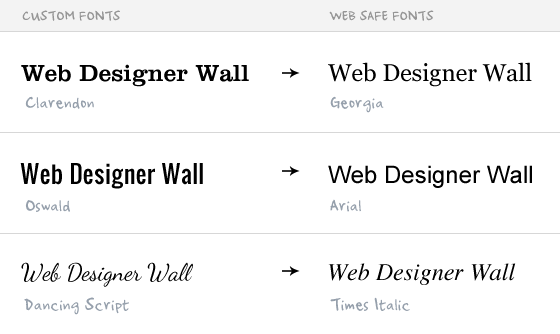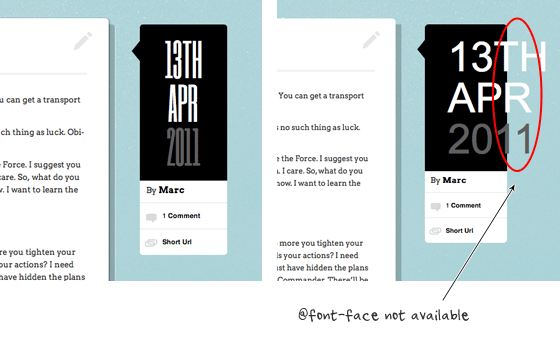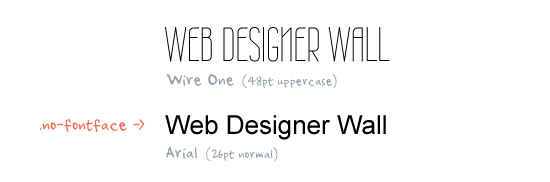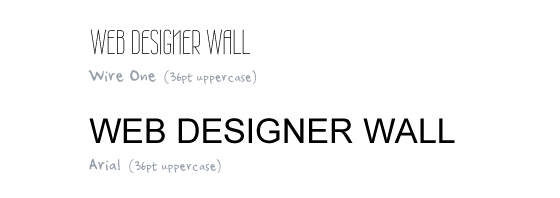
Использование свойства CSS3 @font-face
Хотя свойство @font-face поддерживается большинством браузеров, например, браузерами Internet Explorer, Firefox, Chrome и Safari, есть и исключения. И когда это свойство не поддерживается, то нестандартные шрифты могут испортить верстку или привести к другим нежелательным последствиям. В этом уроке мы расскажем о распространенных сложностях, возникающих при использовании нестандартных шрифтов и подборе запасных шрифтов, присутствующих во всех системах, и покажем, как создать отличные запасные шрифты с помощью библиотеки JavaScript под названием Modernizr.
Распространенная ошибка
Одной из распространенных ошибок при использовании нестандартных шрифтов является то, что многие не определяют запасные шрифты или выбирают неподходящие запасные шрифты.
Запасные шрифты
Присутствующие во всех системах шрифты для обходного пути
При использовании нестандартных шрифтов важно добавить присутствующие во всех системах шрифты в качестве обходного пути. Такой запасной шрифт поможет Вашему дизайну приемлемо выглядеть, когда свойство @font-face не поддерживается или не доступно. Самое важное при выборе запасных шрифтов — выбрать присутствующие во всех системах шрифты, которые наиболее близки к нестандартному шрифту. Например, если нестандартный шрифт — Clarendon, то наилучшим присутствующим во всех системах запасным шрифтом будет Georgia, так как оба эти шрифта с засечками, и у них примерно одинаковая ширина символа.
Сложности с версткой
Так как у каждого шрифта свои ширина, высота, толщина, расстояние между символами и т. д., то некоторые шрифты невозможно заменить присутствующими во всех системах шрифтами. Давайте рассмотрим пример ниже. Это сравнение нестандартного шрифта Wire One и присутствующего во всех системах шрифта Arial размера 36 точек и всеми заглавными буквами.
Это может вызвать сложности с версткой, показанные на изображении ниже, где запасной шрифт вылазит за границы.
Modernizr
К счастью, библиотека JavaScript под названием Modernizr может помочь решить вышеописанные сложности. Modernizr — это библиотека JavaScript, которая определяет, какие свойства CSS3 поддерживаются браузером. После чего добавляется класс CSS в элемент <html>, чтобы показать, поддерживаются ли свойства. Например, если свойство @font-face не поддерживается, добавится класс no-fontface в элемент <html>, т. е. <html class="no-fontface">. Эти классы CSS добавляются с помощью JavaScript, они не видны в исходном коде. Чтобы увидеть их, нужно исследовать элемент страницы или посмотреть созданный код.
Запасные шрифты с помощью Modernizr
Демонстрация работы
Так что мы можем использовать библиотеку JavaScript под названием Modernizr, чтобы определить, поддерживается ли свойство @font-face, и после этого задать подходящие запасные шрифты. Например, можно задать стили для запасных шрифтов, такие как размер, расстояние между символами, толщина, преобразование текста и т. д, чтобы они были наиболее похожи на используемый нестандартный шрифт.
Подключение Modernizr
Стили CSS для класса .no-fontface
После этого нужно добавить дополнительные правила, определяющие стили для класса .no-fontface. Посмотрите пример, чтобы увидеть окончательный результат.
/* wire one font */
h1 {
font-family: 'Wire One', arial, serif;
font-weight: bold;
font-size: 48px;
letter-spacing: 1px;
text-transform: uppercase;
}
/* no-faceface fallback */
.no-fontface h1 {
font-family: Arial, Helvetica, sans-serif;
font-weight: normal;
font-size: 30px;
letter-spacing: 0;
text-transform: none;
}